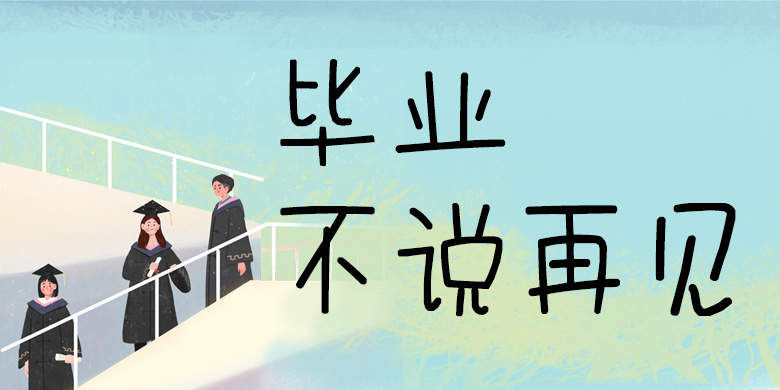
品牌:方正手迹设计师:俞亦婷发行时间:2018字库编码:大陆简体(GB2312-80)分类:创意书写字体属性:精品字
毕业不说再见体,字形头大身小,转折处方圆相济,朝气蓬勃,充满青春活力,让我们毕业不说再见,青春永不散场。适用于青少年儿童类、文艺类书刊、漫画综艺字幕、品牌广告和产品包装设计,以及社交网络的个性化用字。